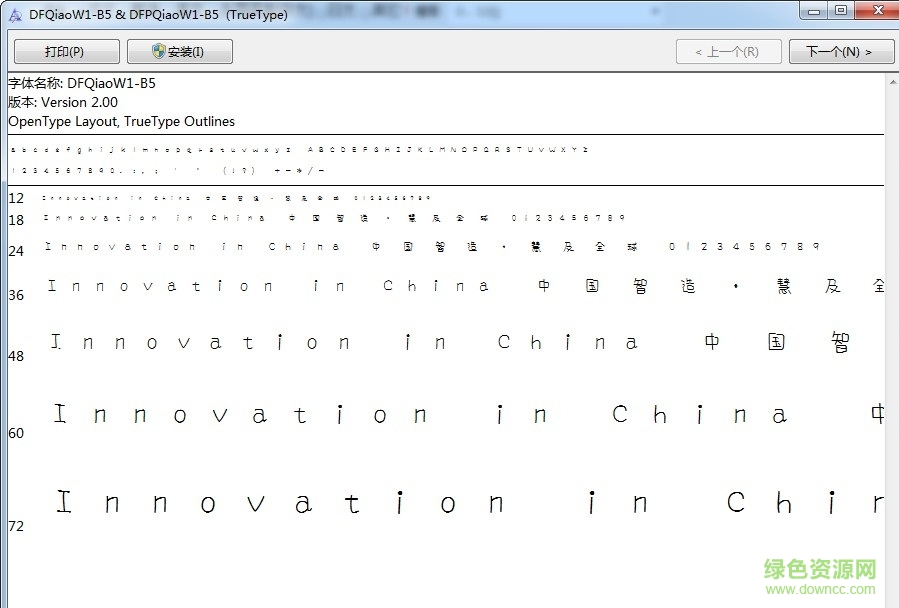
華康巧風(fēng)體字體是一款趣味性較足的字體哦,這款字體看起來非常輕巧,并且字形也很清新,有需要的就來綠色資源網(wǎng)下載吧!
華康巧風(fēng)體,這字體是一款美術(shù)風(fēng)格的繁體字庫,摘自華康最新出品的《華康手書風(fēng)II-字得其樂》,字庫為大五碼(BIG5),臺港澳地區(qū)的繁體系統(tǒng)中使用,所以如果在簡體中文系統(tǒng)中使用時,必須直接輸入繁體字,才能正常顯示所有的文字,并且在字體選擇欄中顯示的字體名稱不是中文,顯示名稱為:DFQiaoW1-B5或DFPQiaoW1-B5。